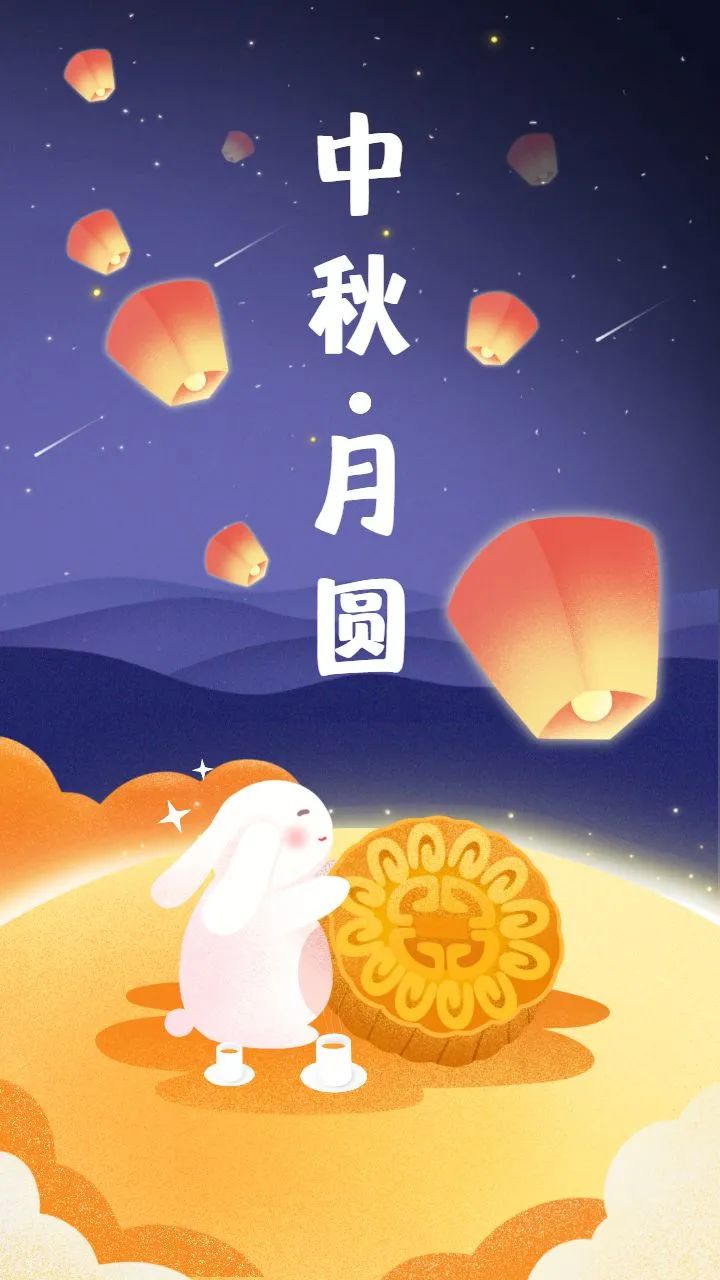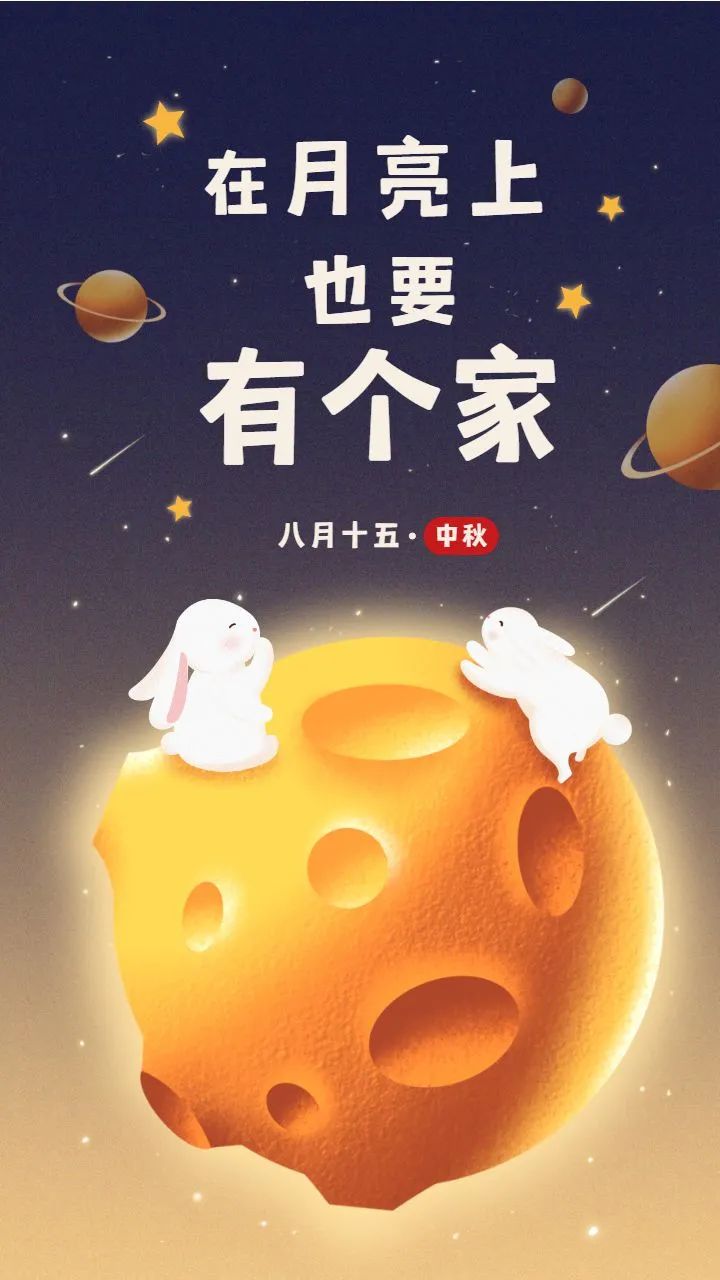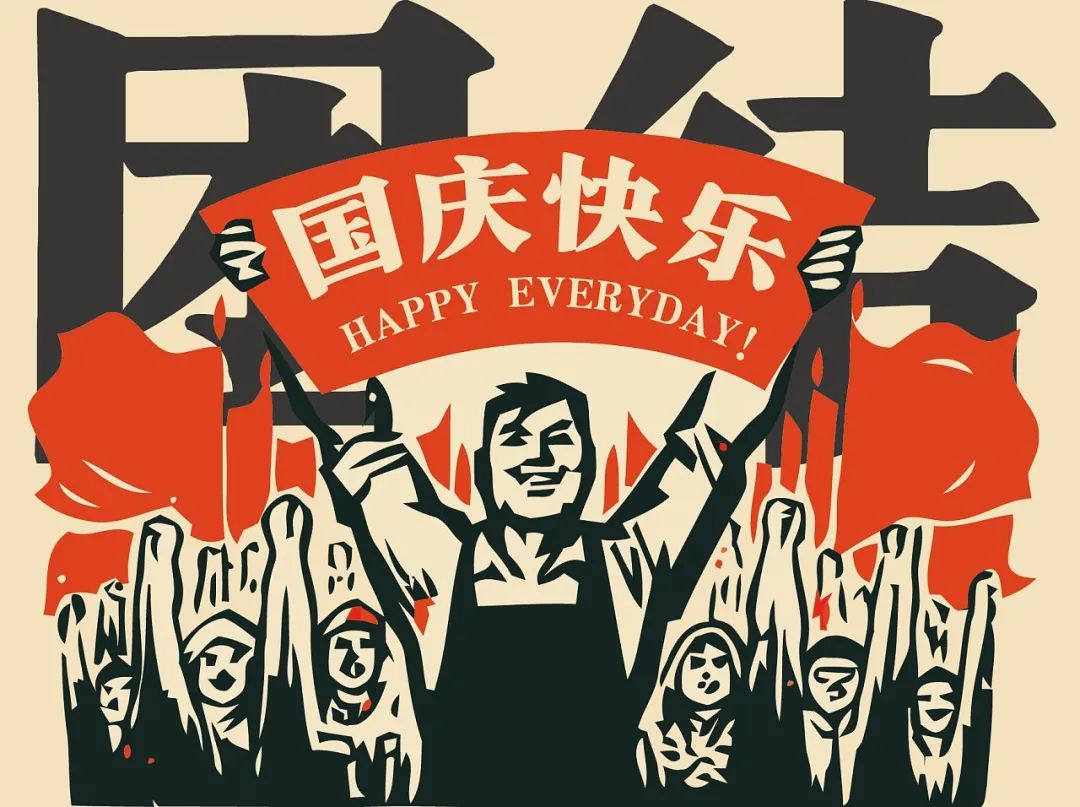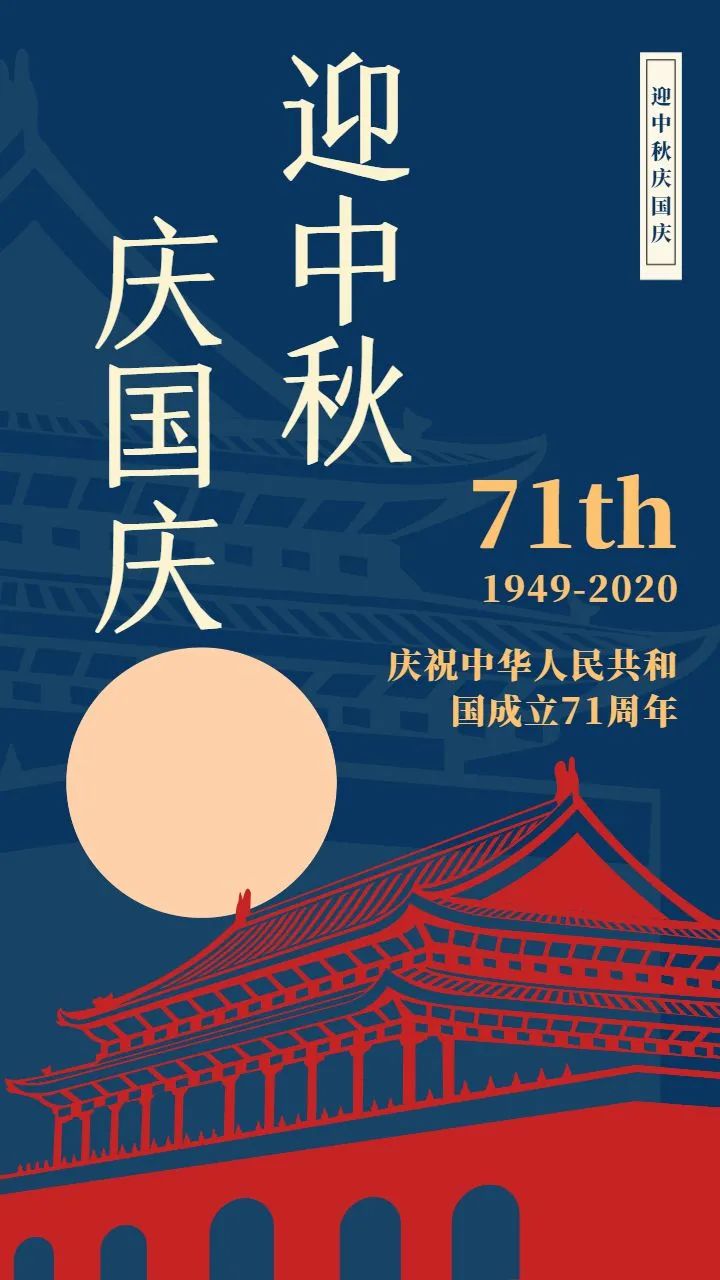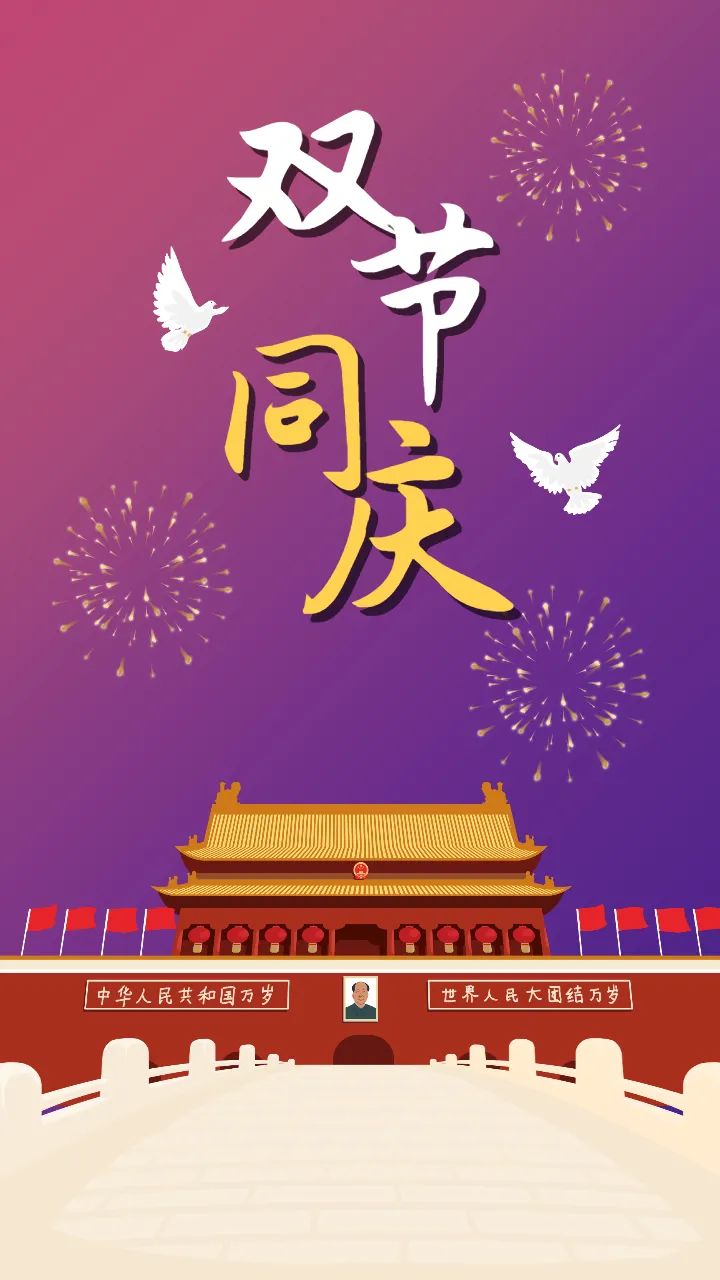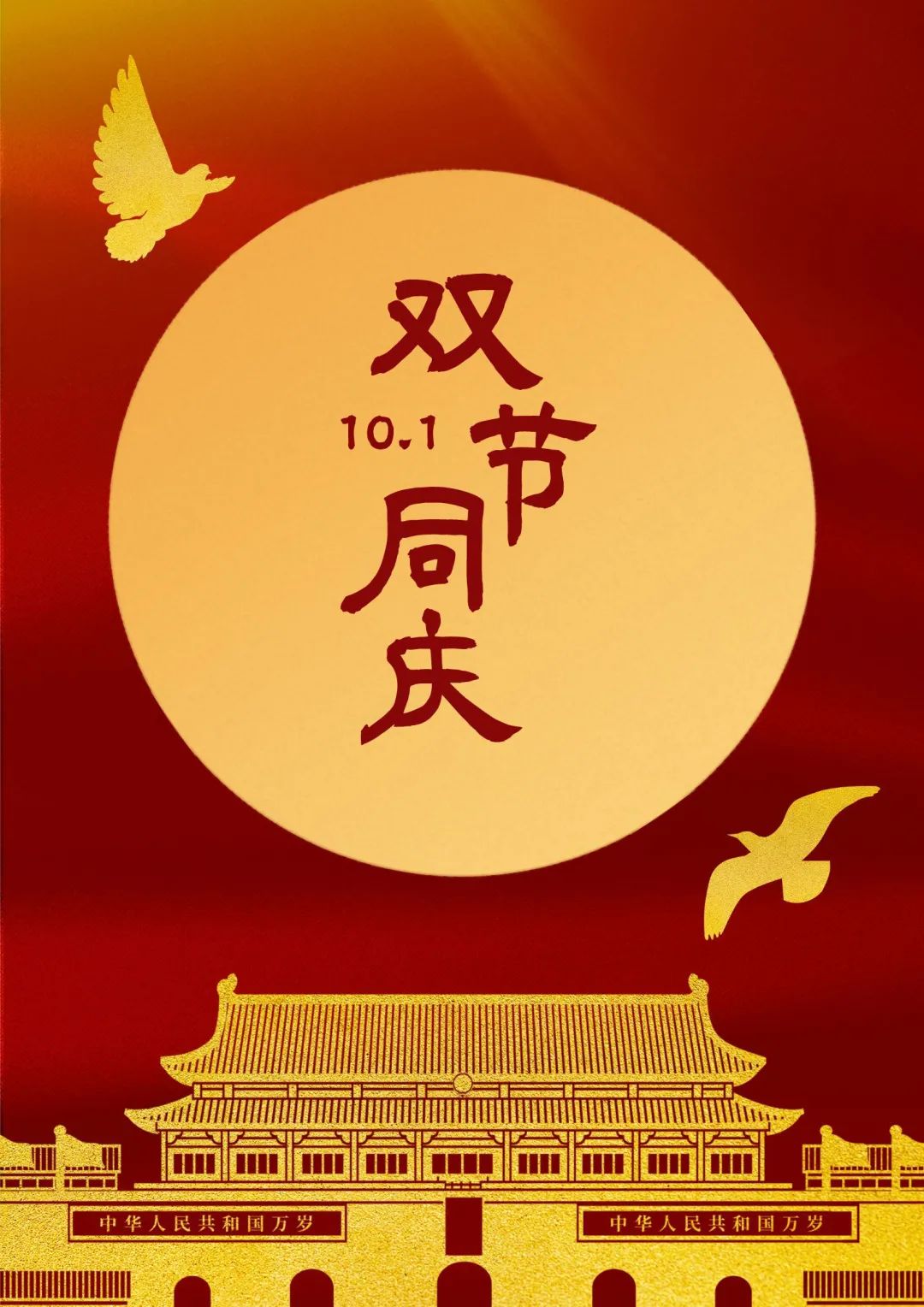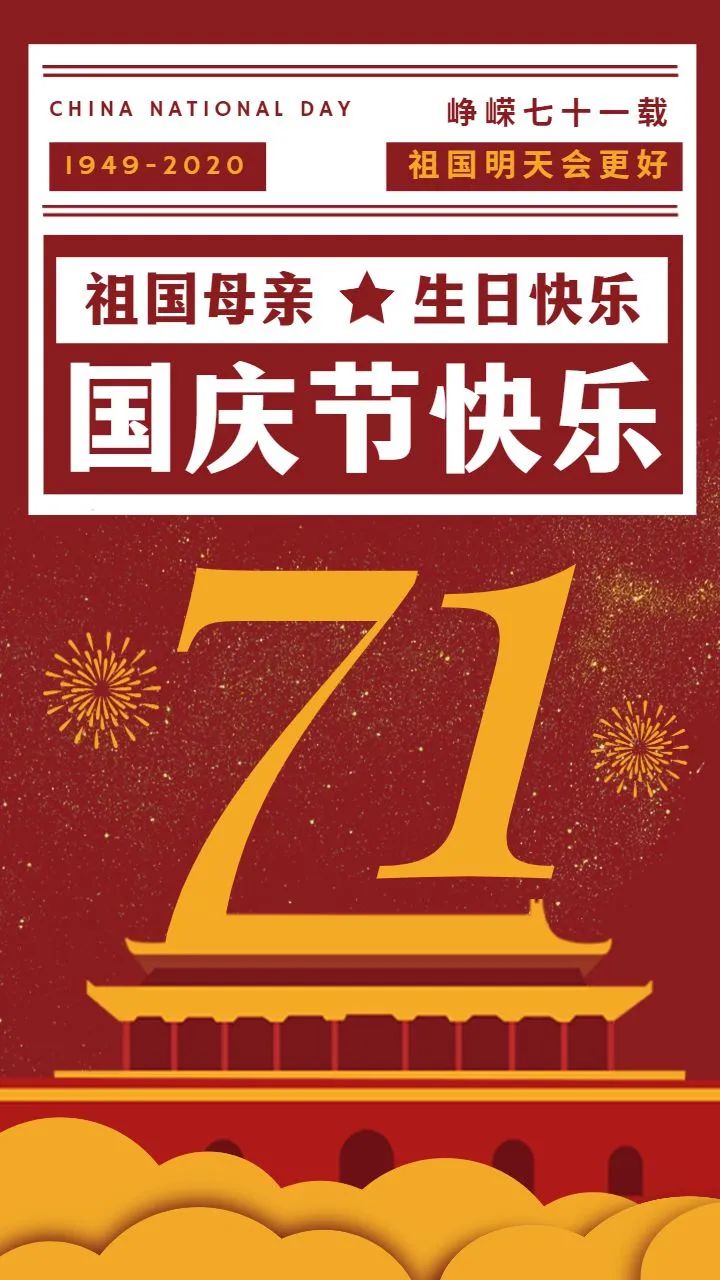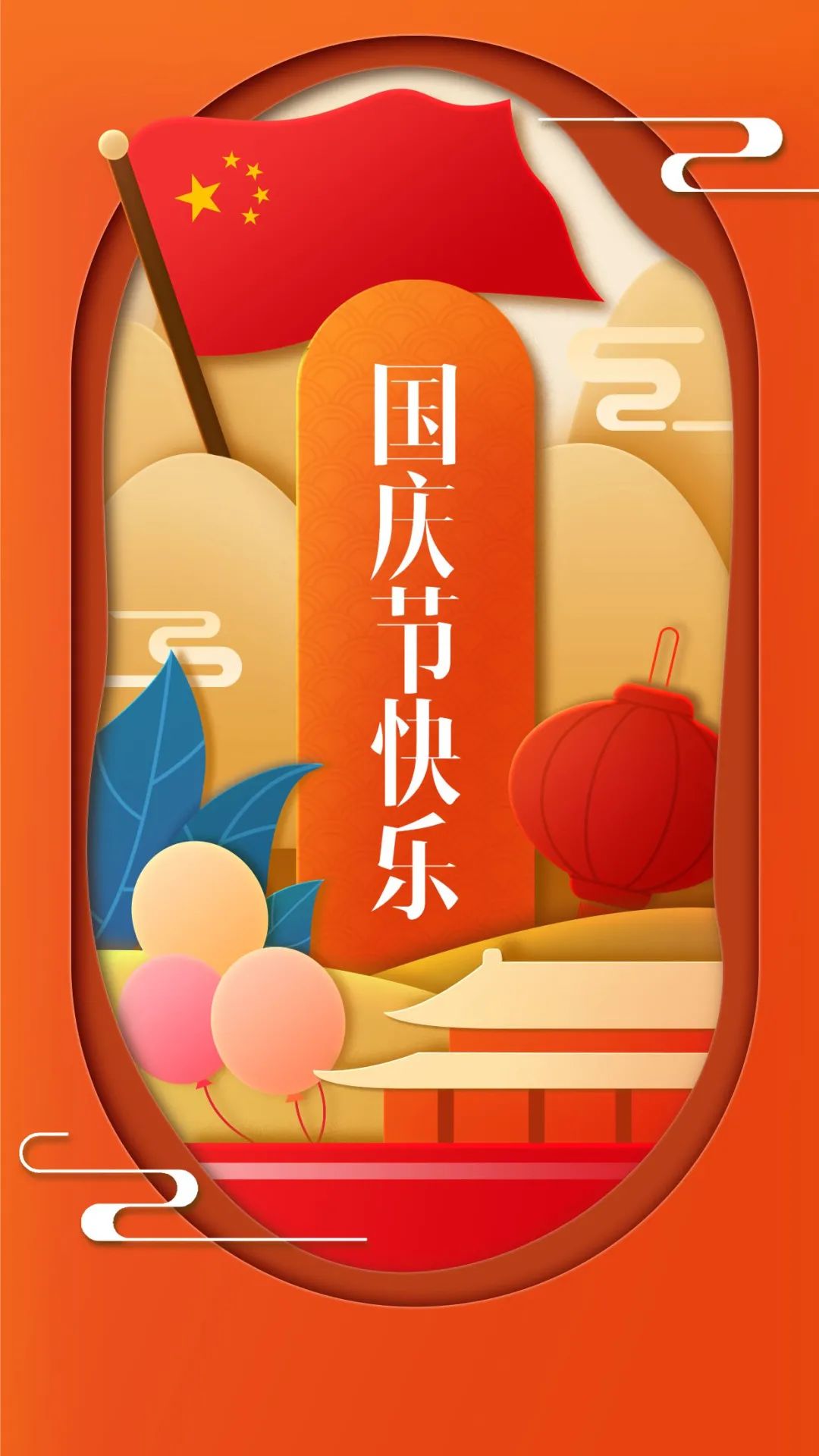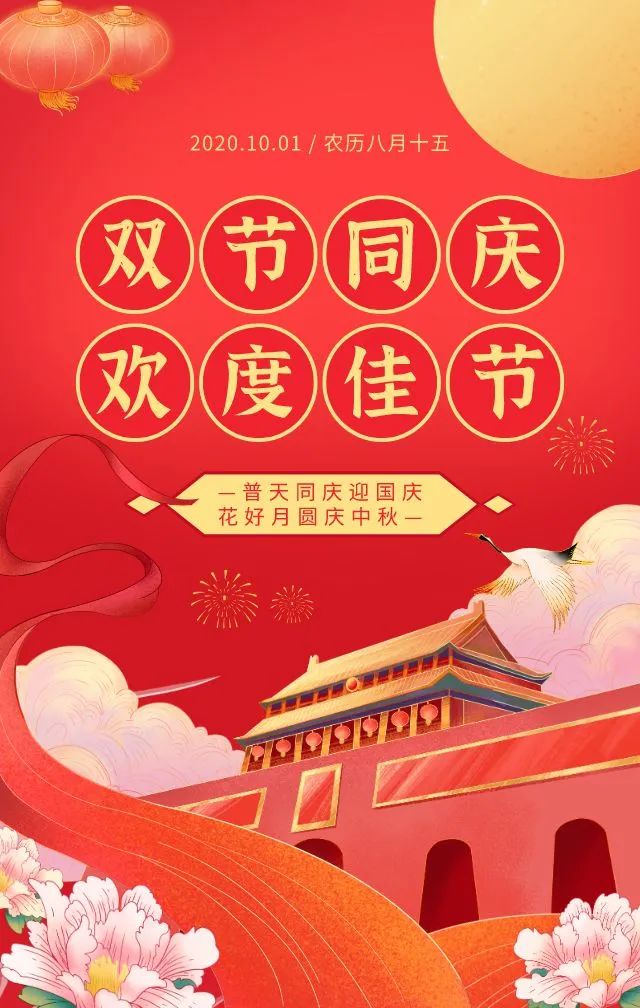
当中秋“撞”上国庆,我突然不会选字了?
不过双节相遇,难度也随之提升,不信你康~
是只做中秋?
还是只做国庆?
或是把两个节日融合在一起?
怎么选择合适的字体?
……
问题层出不穷,感觉纠结症要爆发了,今天柚子就帮帮你。
中秋团圆
如果你明确了中秋主题,在字体选择上可以偏温暖感,比如适合女人和儿童的字体。
国庆气氛
每年十一都是祖国的生日,所以为了普天同庆的气氛,一定要选择醒目,镇得住的字体!
双节同庆
前面分别说了中秋和国庆的用字,如果你想把它们融合在一起,就要找共同点,比如传统感。